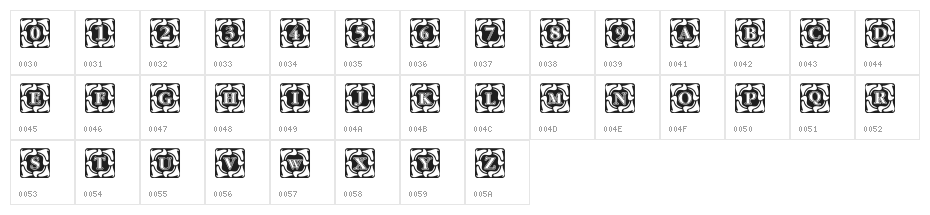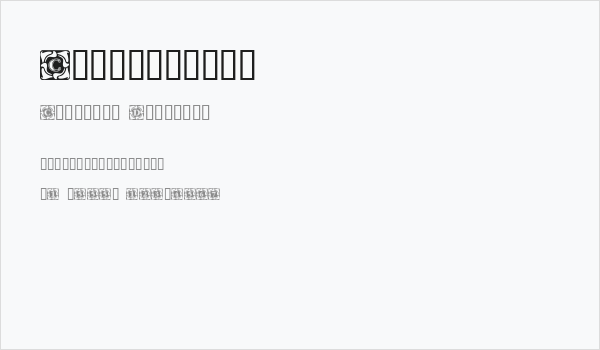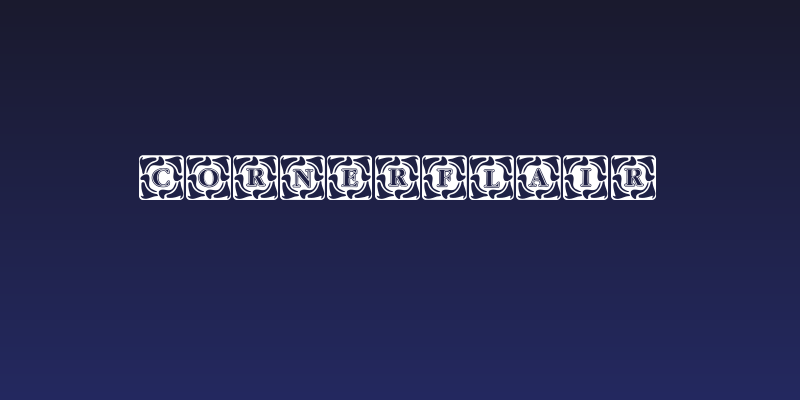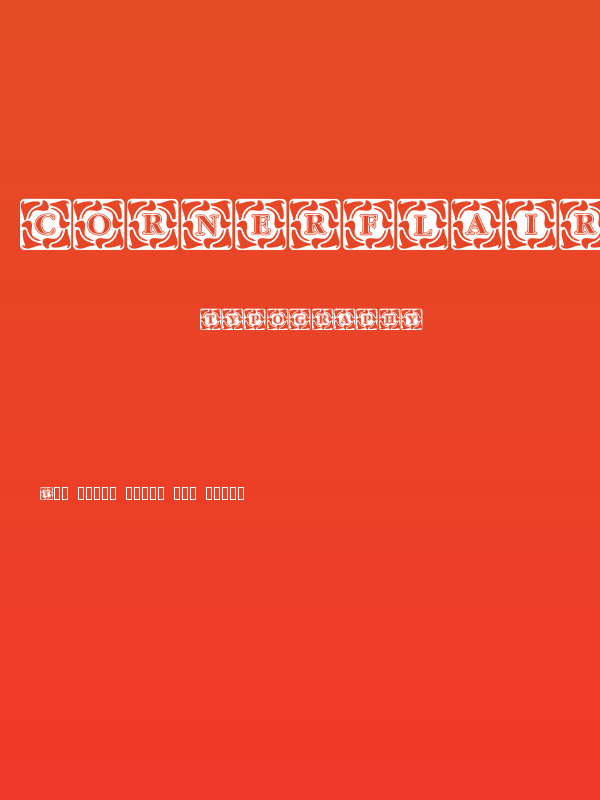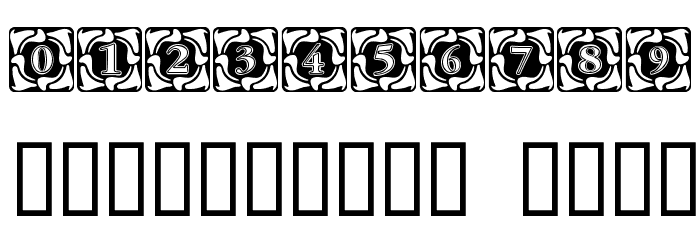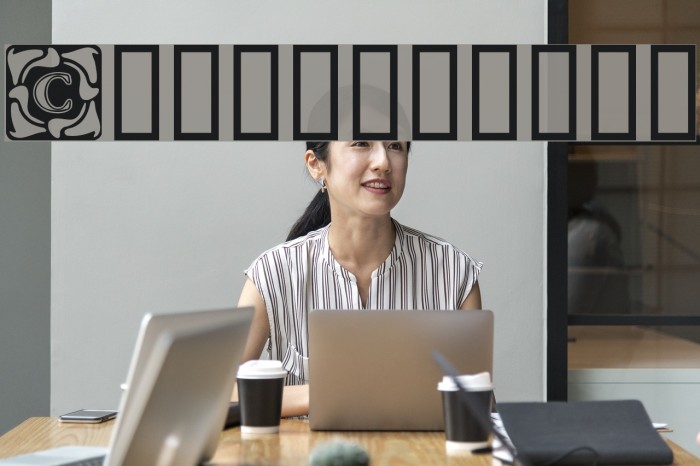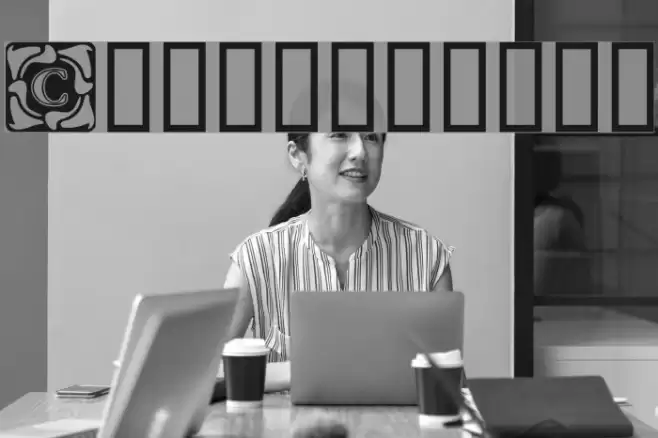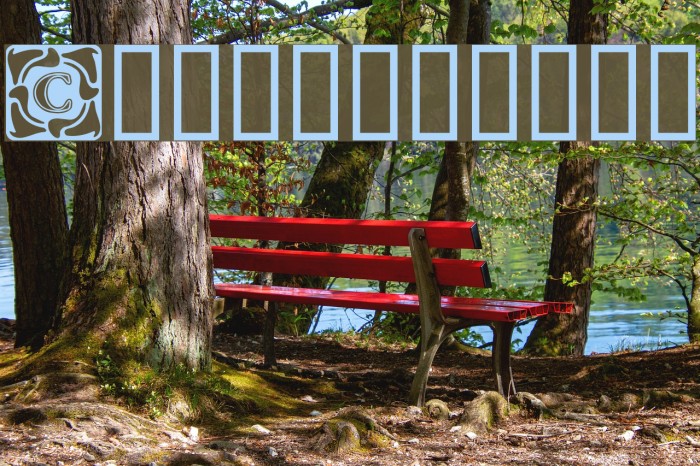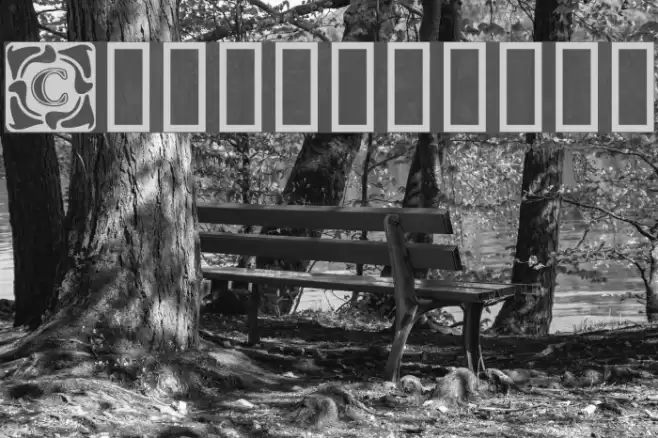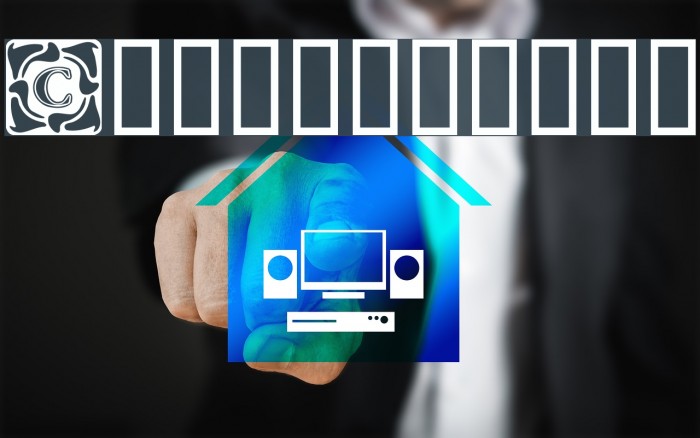
Cornerflair Font
| Gesamtstil | Vintage |
| Anwendungsfall | Logos, Headlines, Decorative text |
| Vorgeschlagene Projekte | Ideal for wedding invitations, luxury branding, vintage posters, and decorative signage. |